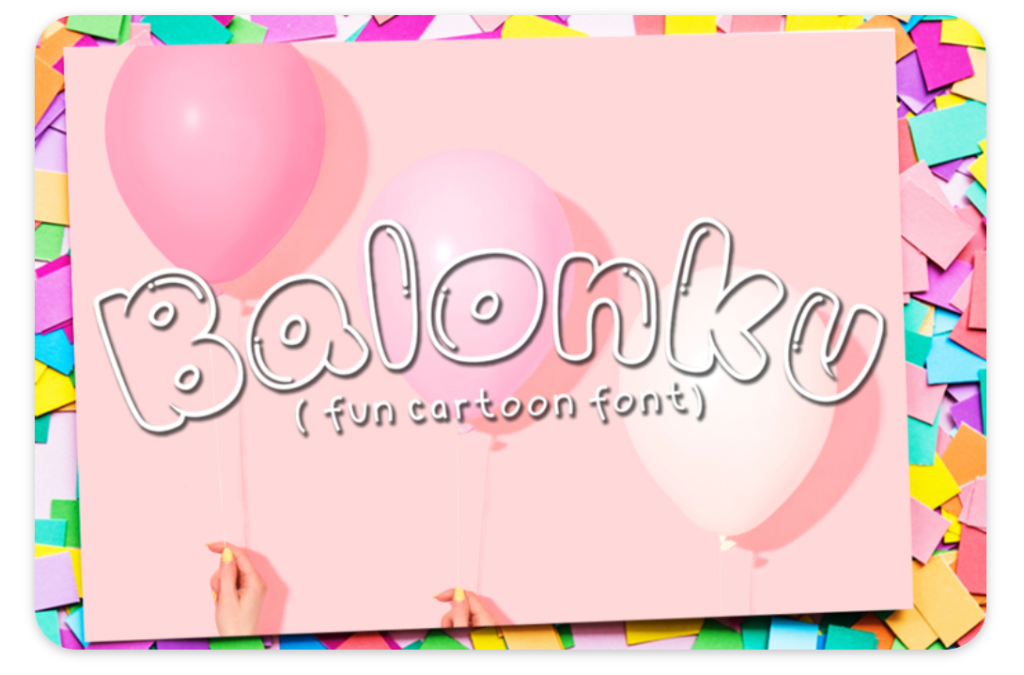
Birthday Font Style
Birthday Font không chỉ là những kiểu chữ, mà còn là những câu chuyện được kể qua từng nét vẽ tinh tế. Bộ font chữ sự kiện này mang đến sự đa dạng phong cách, từ những font chữ đáng yêu, ngọt ngào đến những font chữ sang trọng, lịch lãm, giúp bạn tạo nên những thiết kế sinh nhật thật độc đáo.